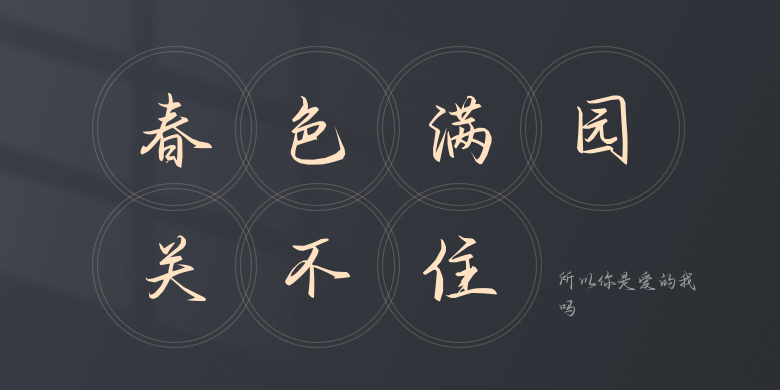
所以你是爱的我吗
所以你是爱的我吗,这款字体结构工整、笔画清晰,兼顾美观与易读性,适用于标题、正文、海报、包装、LOGO 等多种场景。字形优雅稳定,风格百搭耐看,适配日常排版与创意设计,让文字呈现更舒适、更具质感。所以你是爱的我吗一笔一画,皆是细节,以均衡的比例、流畅的线条打造舒适视觉体验,字形端正大气,风格简约现代。无论是商业设计、品牌宣传还是日常排版,都能轻松驾驭,让文字更有格调与力量。所以你是爱的我吗字体下载。